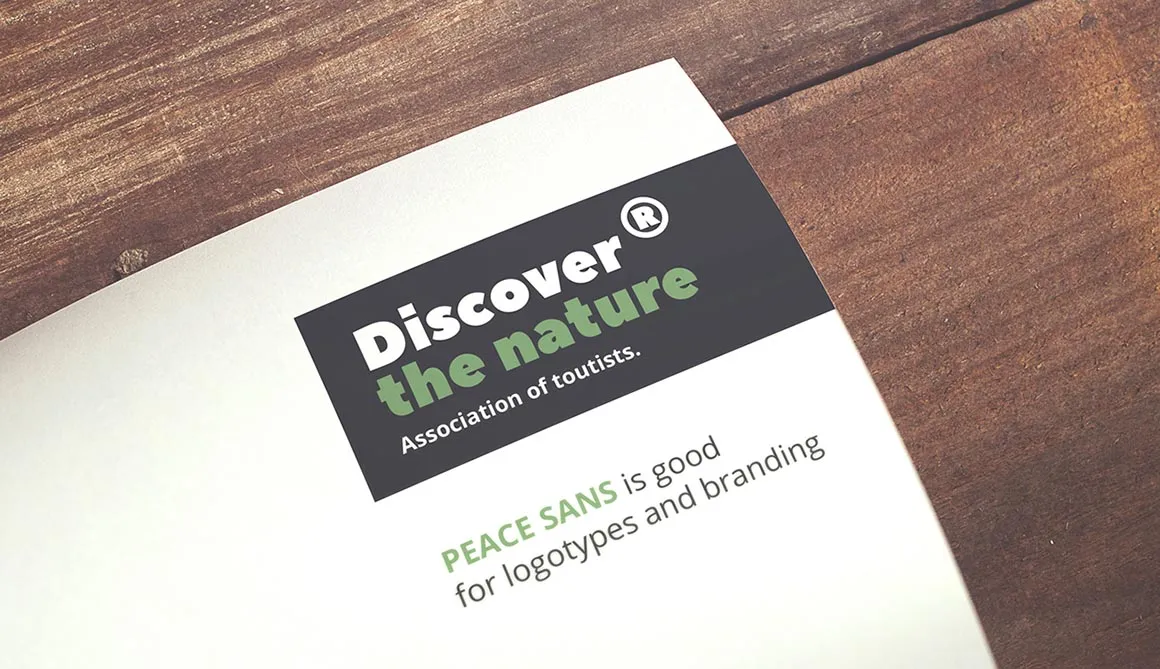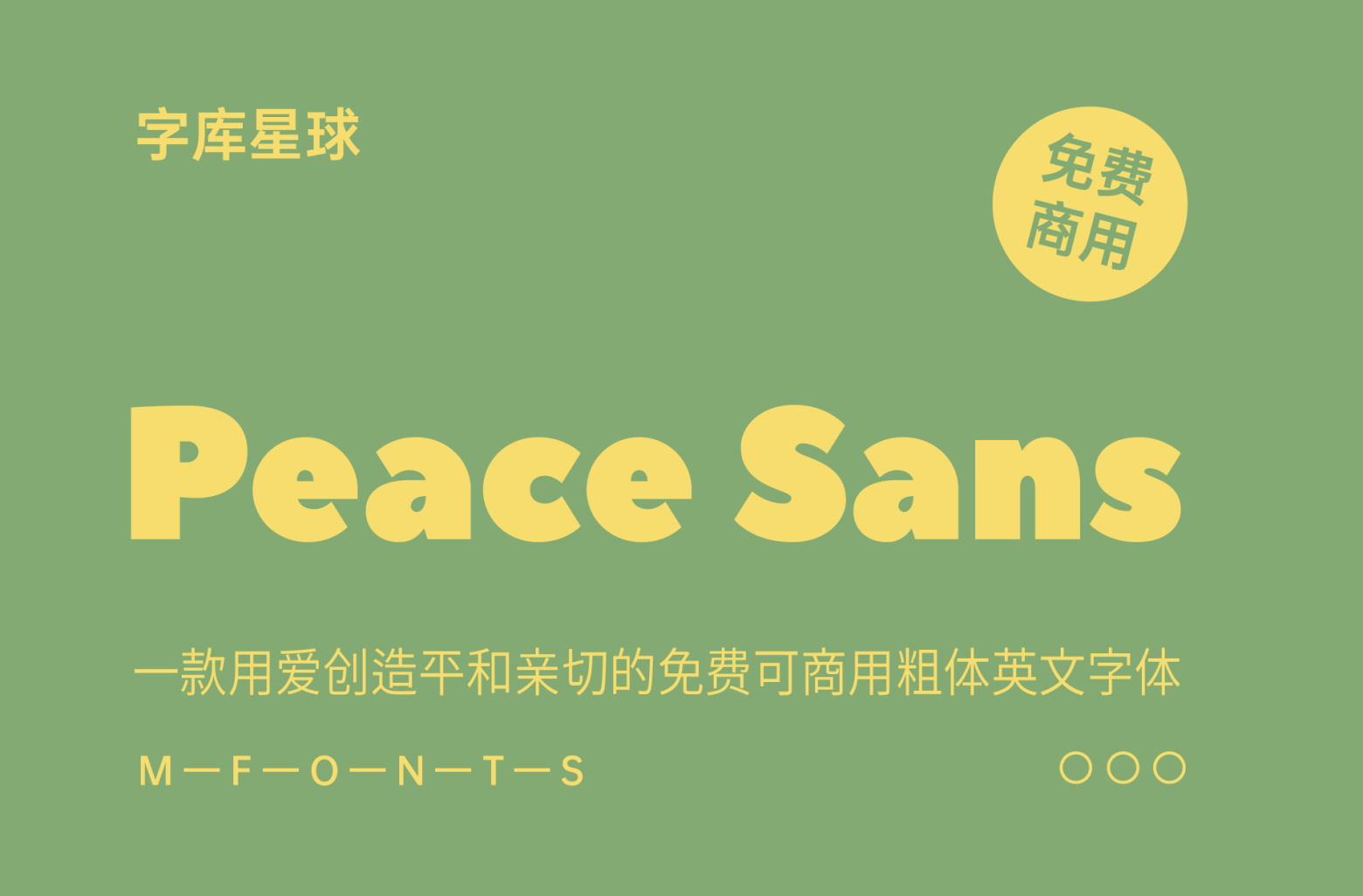
Peace Sans
Peace Sans Font是一款用爱创造的免费可商用粗体英文字体!它可以使你的排版更加和平和亲切。以任何方式使用它,它绝对免费。它是在TypeType School的学习过程中创建的字体。
Peace为您提供了多种组合和排列每种字体的方法,使您能够创建引人注目的现代排版设计。